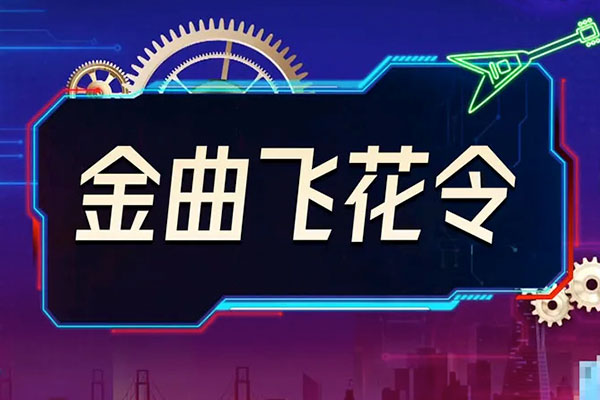
字体圈欣意冠黑体3.0
字体圈欣意冠黑体是邹乐伟设计师的杰出作品,其硬朗潇洒的字形自2.0版本发布以来,便得到了广泛的应用。今天,我们高兴地宣布,他为我们带来了全新的3.0版本,依旧免费商用。
那么,新版3.0都更新了些什么呢?
1. 部分字形设计进行了改进,更具美感。
2. 西文数字标点部分进行了重新设计,更加合理。
3. 新增了3000多个繁体字符。现在,整套字符集将近10,000个。
4. 字形默认大小得到还原,更加自然。
5. 增加了生僻字“biang”。
这次更新的重点是繁体部分。虽然只新增了三千多个繁体字符,比简体数量少了一半,但实际上工作量并未减少。原因是许多繁体字的笔画远比简体多,甚至多达几倍。为免除大家的使用顾虑,邹乐伟设计师提供了免费商用的授权书,我们对他的无私奉献表示感谢!